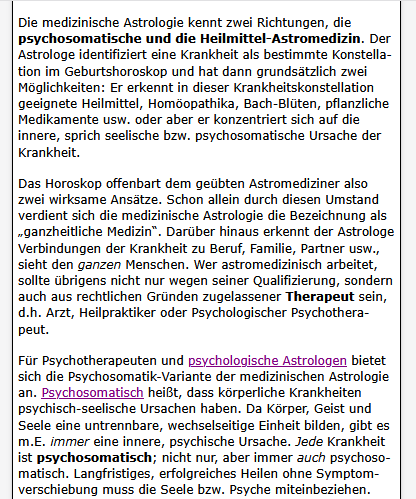
[Verdana] war ja von Beginn an (wie die Georgia, die deutlich besser gealtert ist) eine Schrift und ein Font, der auf Bildschirmen und Rendertechnik von anno dazumal endlich mal brauchbar lesbar war, aber eben mit eigentlich übertriebener x-Höhe, Zeichenbreite und aufwendigem Hinting. Das war damals echt ein Wurf, weil Arial und Times alles andere als bildschirmtauglich waren, aber gestalterisch war da natürlich nie ein Anspruch auf irgend eine Ästhetik da. Heute haben wir höher aufgelöste Bildschirme und wesentlich bessere Raster-Algorithmen, und da kommt dann die volle »Pracht« der Verdana zum Vorschein, und sie überkompensiert die Probleme, die heute nicht mehr akut sind.
Die Pro-Version entschäft das Brachiale des Originalentwurfes durch ihre schmalere Subfamilie und die zusätzlichen, leichteren Schnitte vorzüglich, ohne den Verdana-Charakter zu verlieren. Obwohl keine Geometrische, haben die Condensed-Schnitte für mich ein wenig von der Nobel (ich kann gerade nicht definieren, warum – es ist die Textur).
Mit ein wenig Geschick ist damit für meine Begriffe zeitgemäßes Design möglich – über die originale Verdana würde ich das nicht sagen.
Aber keine Frage: es gibt deutlich handzahmere Schriften.
(Abgesehen davon, dass @Martinus seine Website nicht für die schmaleren und leichteren Schnitte optimiert hat und diese darum vermutlich auch nicht einsetzen wird. Mein Einwurf ist somit fürs Protokoll, nicht für den Thread)
Das war ja von Beginn an (wie die Georgia, die deutlich besser gealtert ist) eine Schrift und ein Font, der auf Bildschirmen und Rendertechnik von anno dazumal endlich mal brauchbar lesbar war, aber eben mit eigentlich übertriebener x-Höhe, Zeichenbreite und aufwendigem Hinting. Das war damals echt ein Wurf, weil Arial und Times alles andere als bildschirmtauglich waren, aber gestalterisch war da natürlich nie ein Anspruch auf irgend eine Ästhetik da. Heute haben wir höher aufgelöste Bildschirme und wesentlich bessere Raster-Algorithmen, und da kommt dann die volle »Pracht« der Verdana zum Vorschein, und sie überkompensiert die Probleme, die heute nicht mehr akut sind.
Ich wüsste eigentlich nicht, in welchem Fall die Open Sans, die ja auch »nur« ein Frutiger-Me-Too ist, wie die Verdana, wie die Segoe oder die Myriad, etc. etc., nicht die bessere Wahl wäre, und für die es eine unkomplizierte Lizenz auch für Selfhosting gibt. Wenn das hauptsächliche Problem ist, dass ein Schriftwechsel das bestehende Layout (zer)stört, dann ist (im Web) die Layout-Technik nicht richtig gedacht: es gibt heute defacto keine 4 »breakpoints« mehr, an denen man sich orientieren kann, sondern so viele Fälle, dass jede Optimierung auf bestimmte Breiten zum Scheitern verurteilt ist (das sind keine Exoten die wissen was sie tun). Einigermaßen verlässliche Breakpoints waren 201x, wir sind wieder (fast wie 1996) »fluid«, nicht responsive unterwegs, zumindest was Schrift und Typografie betrifft. Nur zum Glück mit viel viel besseren Steuermöglichkeiten, was die umgebenden Boxen betrifft, die die Texte enthalten (flex, grid, container-queries und -units, ...), damit das Umfeld der (frei fließenden) Texte nicht entgleist und somit steuerbare Typografie unmöglich machen würde.
Ich würde Energie eher da rein stecken das flexibel zu machen, statt alles auf eine Schrift zu optimieren und dann doch noch davon ausgehen zu müssen, dass das bei vielen Betrachtern schlimmer ankommt als etwas das gar nicht optimiert ist – spätestens mittelfristig lohnt sich das.
Georgia bzw. deren free-Ersatz Gelasio habe ich für Überschriften.
Bei mir, also für mittlere Fließtextgrößen und eher nicht hochauflösende Displays sieht Verdana sehr gut aus. Ästhetik ist halt zum einen auch Geschmackssache und zum anderen eine Frage des Einsatzweckes.
Zu hochauflösenden Displays kann ich aber tatsächlich nicht viel sagen. Wie sehen die unguten Überkompensationen denn aus, die vielleicht User mit ihren Smartphones oder FHD/4K-Monitoren wegen der hohen dpi sehen? Wenn da vieles im Argen liegt, was die User erleben und ich nur nicht kenne, dann wäre das ein Grund gegen Verdana. Denn viele sind hochauflösend unterwegs, v.a. mit Smartphones vermutlich.
Hat die neue Verdana Pro denn diese Probleme nicht gelöst?
Ich habe mal zwei screenshots von Text im kleinsten Smartphone-Viewport aus meiner Testumgebung angehängt, der eine mit Verdana, der andere mit (bez. Hinting und Kerning für alle Schriftgrößen und dpi gut optimierten) Inter, ein Px größer. Die Zeilenhöhe ist beim einen etwas mehr, das müsste man sich wegdenken für einen fairen Vergleich. Nur mal so zum Vergleich, der angesichts des fehlenden HW-Aspekes/Auflösung und eines simplen screenshot-Bildes nur als Vergleich zwischen beiden Aussagekraft hat.
Meine Seiten sind mit einem dreispaltigen Grid, mehreren Media Queries und durchgehend fluide gebaut. Die Seiten sind nicht "alles auf die Schrift hin ausgerichtet", aber nach mehreren Monaten bin ich jetzt fast fertig und habe das mit den Systemschriften erst jetzt bemerkt. Jetzt möchte ich weitgehend metrisch kompatible Schriften, die nicht wieder alles ändern. Das ist ein ganz normales Anliegen, das Webdesigner (der ich nur hobbymäßig bin) bestimmt öfters haben.
Open Sans habe ich auch schon probiert. Ich müsste sie wie Inter 1px erhöhen, aber da hat etwas nicht gepasst.